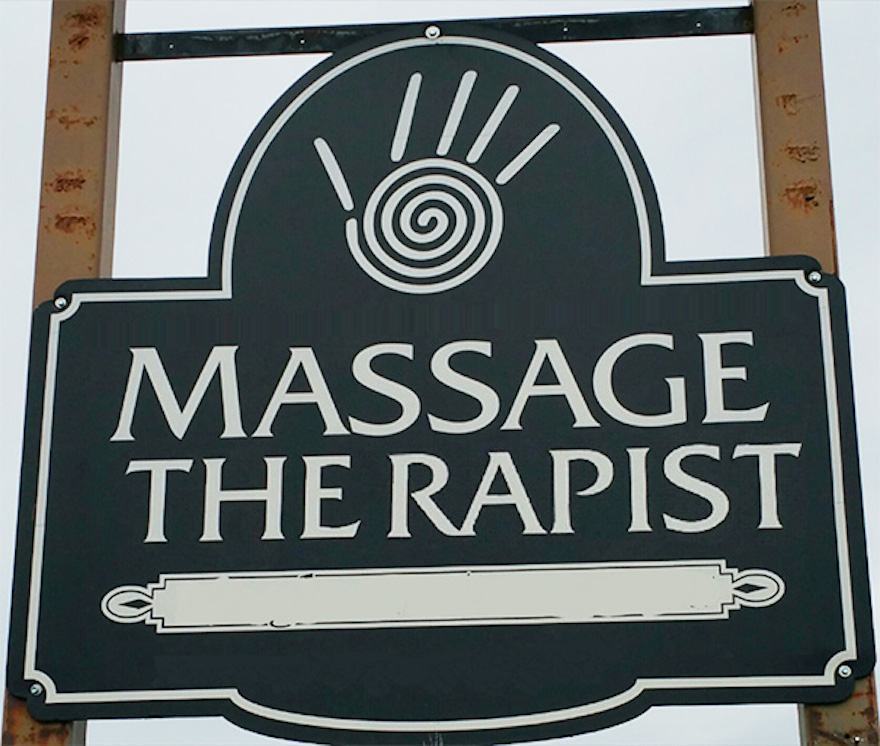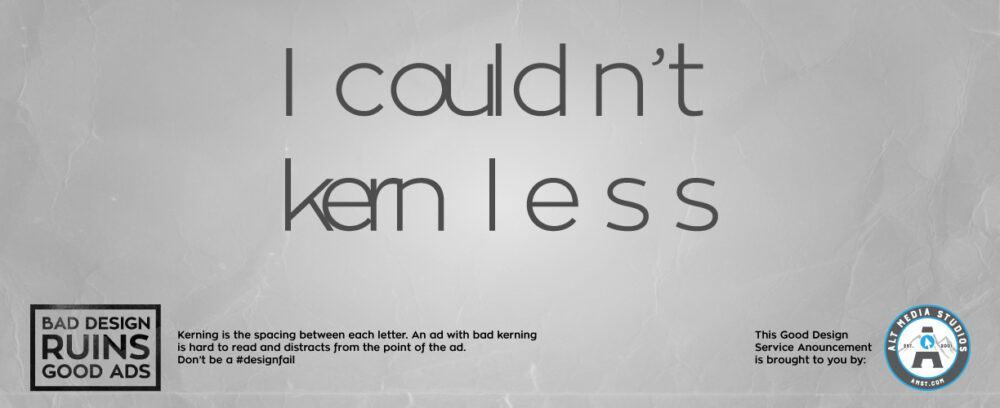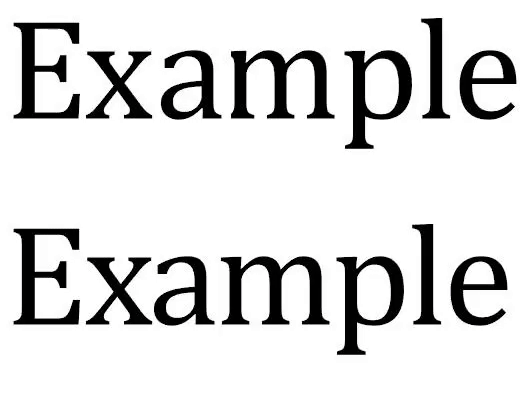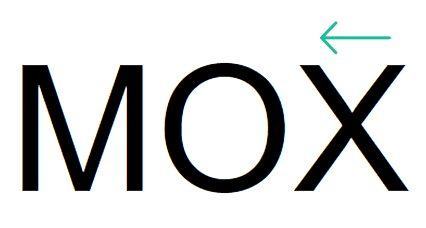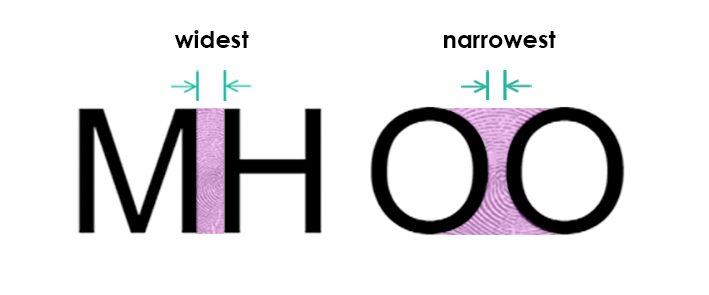
Kerning là gì? Cách sử dụng Kerning cho Font chữ trong thiết kế Typography?
Đầu tiên chúng ta hãy xem một ví dụ thông qua bức ảnh này nhé! Không cần đến kinh nghiệm của một Designer chuyên nghiệp, bạn cũng có thể nhận thấy một điều hơi sai trong tấm hình này:
Đó chính là phần văn bản nằm khá gần với logo một cách chưa phù hợp.
Sau khi điều chỉnh khoảng cách của văn bản và logo, tấm hình trông đẹp hơn nhiều. Nhưng nếu người thiết kế bảng hiệu này là một chuyên gia được đào tạo bài bản, chúng ta sẽ có một vấn đề khác.
Trước hết chúng ta cần biết về các thuật ngữ có trong tiêu đề:
Typography là một nghệ thuật thiết kế, sắp xếp và sáng tạo hình dáng của các chữ cái sao cho thiết kế có tính thẩm mỹ, thể hiện một phong cách nhất định. Công việc này bao gồm thiết kế kiểu chữ (typeface), cỡ chữ, độ giãn cách và trang trí. Các thuật ngữ cơ bản trong một thiết kế Typography gồm có:
Leading là khoảng giãn giữa 2 dòng.
Hierarchy thì các thông tin quan trọng sẽ được để lớn hơn, đậm hơn so với những thông tin mang tính phụ.
Tracking được dùng để biểu thị độ dài của một từ.
Kerning là một quá trình điều chỉnh khoảng cách giữa các ký tự trong một phông chữ, được dùng trong thiết kế để ấn phẩm trở nên dễ nhìn và bắt mắt hơn.
Kerning là gì?
Văn bản ngày càng trở thành trọng tâm trong một thiết kế, mắt chúng ta dễ bị thu hút và cũng dễ dàng cảm nhận được những khuyết điểm nhỏ trong đó. Và một trong những khuyết điểm phổ biến nhất trong thiết kế mà bạn gặp, thường nằm ở khoảng trống giữa các chữ cái hay còn gọi là Font Kerning.
Thoạt nhìn qua, nếu bạn là nhà thiết kế chuyên nghiệp, bạn sẽ nhận thấy được sự khác biệt giữa trước và sau của Font chữ. Từ khóa cốt lõi ở đây là “nhận thức”. Tuy nhiên, nếu bạn nhìn theo hướng khoảng trống giữa tất cả các chữ cái trong từ có kích thước bằng nhau, thì bạn chẳng thể nhận ra sự khác biệt. Hãy xem tấm hình dưới đây:
Kerning là thuật ngữ để chỉ khoảng cách giữa 2 chữ cái. Do đó, nếu đặt chúng quá gần hoặc quá xa nhau sẽ khiến cho người đọc cảm thấy khó chịu và không thể hiểu được toàn bộ thông điệp mà bạn muốn truyền tải.
Sau khi áp dụng Kerning, từ “Example” đã cân đối và dễ đọc hơn, mặc dù dưới góc độ hình học, không gian giữa các chữ cái được phân bổ không đồng đều. Trong thiết kế typography, đôi khi nó được gọi là nhịp ngang (horizontal rhythm – khoảng cách theo nhịp điệu giữa các chữ cái).
Mỗi phông chữ được tạo ra đều có nhịp điệu riêng và các yếu tố tạo nên nhịp điệu đó là:
• Các chữ cái — mỗi chữ cái đều có một dấu ấn thị giác riêng trong một từ
• Các yếu tố — độ đậm và độ dài dòng có thể thay đổi khoảng cách của các chữ cái
• Cặp chữ cái — sự tương tác giữa hai chữ cái liền kề
Các chữ cái
Có 5 loại chữ cái:
• Nét thẳng đứng: M, H, N – có các phần tử thẳng đứng ở cả hai bên
• Nét tròn: O
• Nét nửa tròn: B, D
• Mở một nửa: L, E, C, K, J
• Mở toàn bộ: X, T, W
Nếu tất cả các chữ cái đều là nét thẳng đứng, chúng ta nên sử dụng phương pháp Kerning có khoảng cách bằng nhau:
Tuy nhiên, nếu kết hợp các loại chữ cái khác nhau, chúng ta cần thực hiện nhiều biện pháp điều chỉnh hơn để phù hợp với từng loại ký tự:
Thông thường, các ký tự nét thẳng đứng sẽ có khoảng cách rộng nhất, trong khi các ký tự có hình dạng mở sẽ ít hơn.
Có vô số yếu tố trong mỗi kiểu chữ (typeface) có thể làm cho bất kỳ chữ cái nào trở nên độc đáo và những kiểu chữ này đều có tên. Từ các chữ cái có phần dưới (g, j, p, y), có phần trên (b, d, f, h, k, l, t), đường viền chữ, serifs (chữ cái có chân, cổ điển) hoặc san-serif (không có chân, hiện đại), phần đầu cuối của ký tự, góc của chữ cái đến độ đậm của đường nét, v.v. – mọi thứ đều góp phần vào vẻ đẹp của từng kiểu chữ.
So sánh từ này trong 2 phông chữ khác nhau:
Cách hai ký tự đầu tiên “I” và “n” tương tác là hoàn toàn khác nhau trong cả hai trường hợp. Do chân chữ nên chữ cái “I” như bị “ra rìa” trong trường hợp trên. Vì thế để cải thiện tình trạng này khiến cho nó bắt mắt và dễ đọc hơn, GenZ đã đưa chữ “I” lại gần thêm một chút.
Về cơ bản, mọi phông chữ được đưa ra sử dụng đã được nghiên cứu với hàng nghìn tổ hợp hoặc cặp chữ cái khác nhau. Đối với phông chữ web và soạn thảo văn bản, các nhà thiết kế phông chữ đã cố gắng dự đoán tất cả các cặp có thể đứng kế bên nhau, để tạo ra khoảng cách hợp lý. Tuy nhiên, một số cặp chữ nhất định vẫn luôn gây rắc rối ở hầu hết mọi phông chữ, đặc biệt khi ở kích thước lớn như:
Làm thế nào để sử dụng Kerning một cách hiệu quả?
Có rất nhiều phương pháp hình học để sử dụng trong kerning, nhưng điều này quá khó cho với một Designer và đây là nhiệm vụ của các nhà thiết kế phông chữ. Trong bài viết này, GenZ sẽ giới thiệu cho bạn cách sử dụng một kỹ thuật kerning đơn giản: bộ ba (trios).
Đây là từ chúng ta thực hiện Kern (điều chỉnh khoảng cách giữa 2 chữ):
Hãy nhìn lại những thiết kế của bạn và nó có bị mắc lỗi Kerning hay không và hãy luyện tập phương pháp Kerning trong bài viết này để thiết kế của bạn trở nên hoàn hảo hơn nhé!